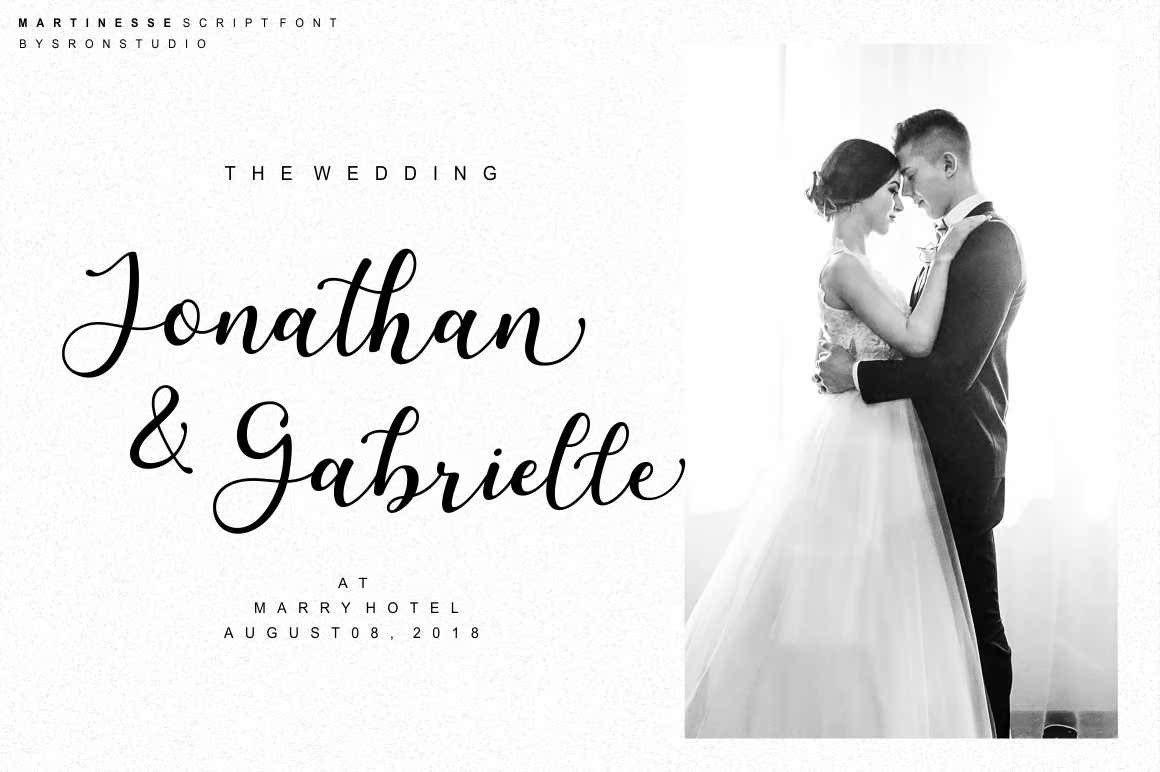
简介艺术–现代和新鲜的ScriptFont,具有优雅的替代品,使这款Font完美地满足任何设计需求、现代活力设计、品牌、文具设计、博客设计、现代装饰设计、邀请函、艺术报价、家居装饰、书籍/封面、邀请函、特价品、生日、定制马克杯、枕头、t恤、,任何画笔书写需求和更多。简介艺术–一款全新的ScriptFont,具有优雅的替代品,可满足任何设计需求、现代活力设计、品牌、文具设计、博客设计、现代装饰设计、邀请、艺术报价、家居装饰、书籍/封面、邀请、特色、生日、定制马克杯、枕头、t恤、,任何笔迹都需要更多。